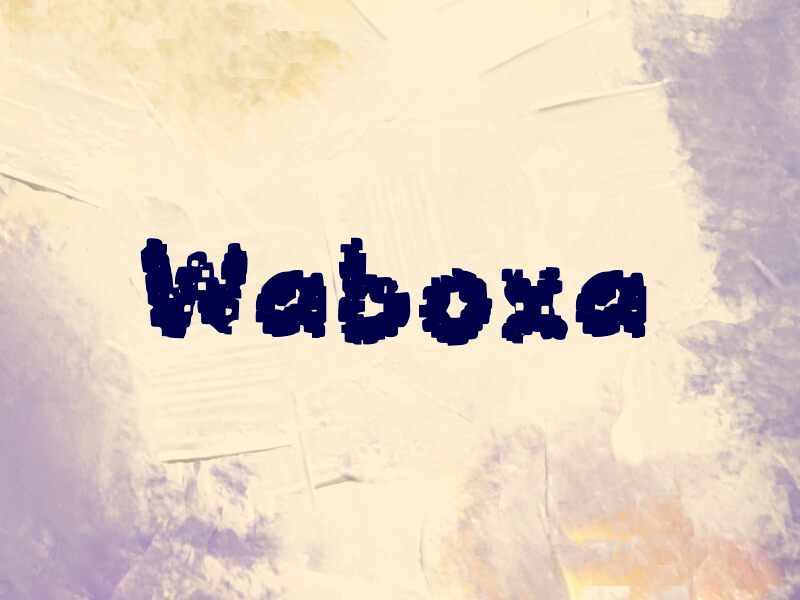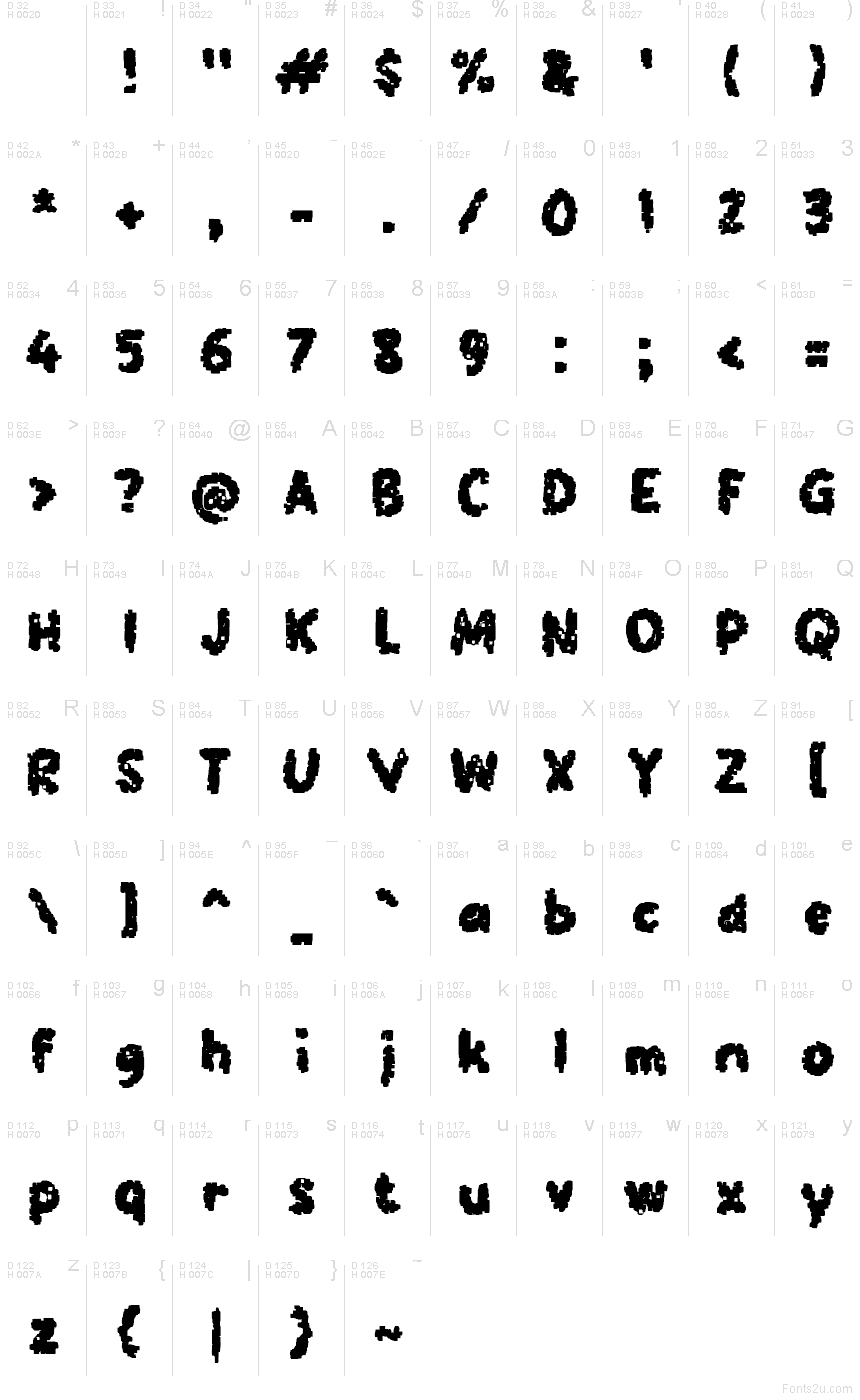
Waboxa от Wep - это бесплатный дисторшн-шрифт, форма которого задается грубыми, рублеными краями: кажется, будто каждая буква была выбита из разбитых кусков материала. Эта шершавая текстура пронизывает весь гарнитур, придавая дизайну коренастый, собранный «с миру по нитке» вид, что выглядит куда интереснее простого волнообразного искажения.
Такая зернистая масса идеально подходит для заголовков на плакатах, обложках альбомов, игровой графике, флайерах и зинах, где буквы должны выступать в качестве графического элемента. Короткие заголовки и логотипы особенно выигрывают от этого «щербатого» прямоугольного ритма, который делает шрифт дерзким и напористым, не превращая его при этом в случайный хаос.
Waboxa
Презентация и наглядный образец шрифта Waboxa
Таблица символов шрифта Waboxa
Таблица символов Waboxa: Базовая латиница, страница 1
Глифы шрифта Waboxa — Базовая латиница, страница 1